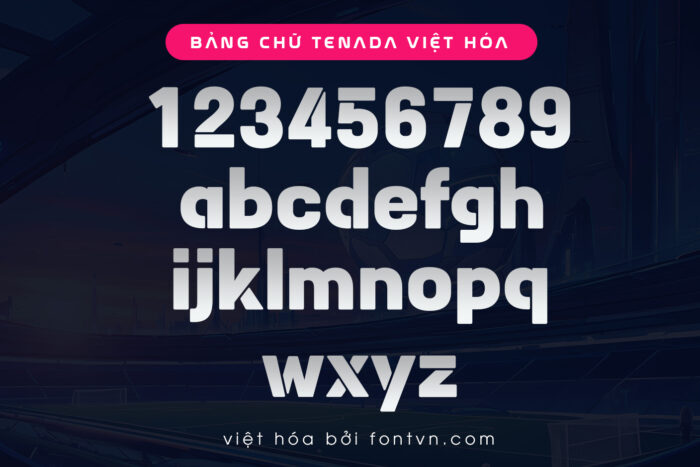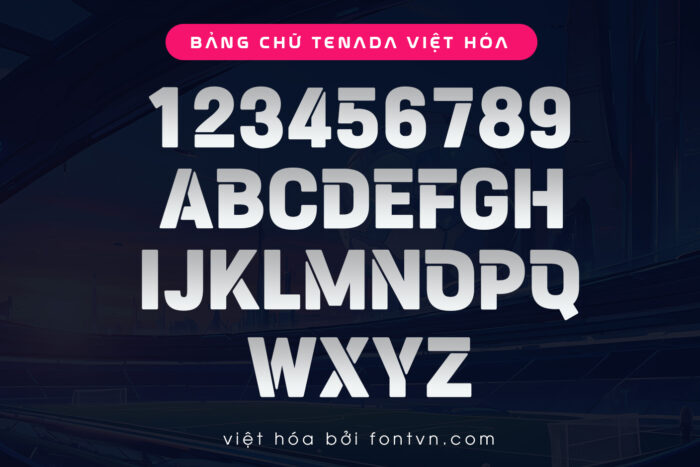
DVN Teneda Việt hóa – Font chữ nét đứt thể thao và năng động
Font chữ “Tenada” là một sự kết hợp hoàn hảo giữa phong cách hiện đại và tính hình học mạnh mẽ. Với các đường nét dày dặn và sắc sảo, font này tạo ra một cảm giác vững chắc và tự tin. Các ký tự trong “Tenada” có độ rộng tương đối đều nhau, tạo nên sự cân đối và dễ dàng nhận diện. Đặc biệt, các góc cạnh được xử lý mềm mại, tạo nên sự hài hòa và mượt mà trong thiết kế, nhưng vẫn giữ được sự cứng cáp và nổi bật.
“Tenada” được thiết kế để thu hút sự chú ý, với khả năng truyền tải thông điệp một cách rõ ràng và mạnh mẽ. Nhờ vào tính chất hình học và sự gọn gàng của nó, font này rất phù hợp cho các tiêu đề, logo, và các thiết kế yêu cầu sự rõ ràng và độc đáo như thiết kế thể thao và các dự án sáng tạo. Nó mang đến một vẻ đẹp hiện đại và chuyên nghiệp, làm tăng thêm giá trị cho bất kỳ dự án thiết kế nào.